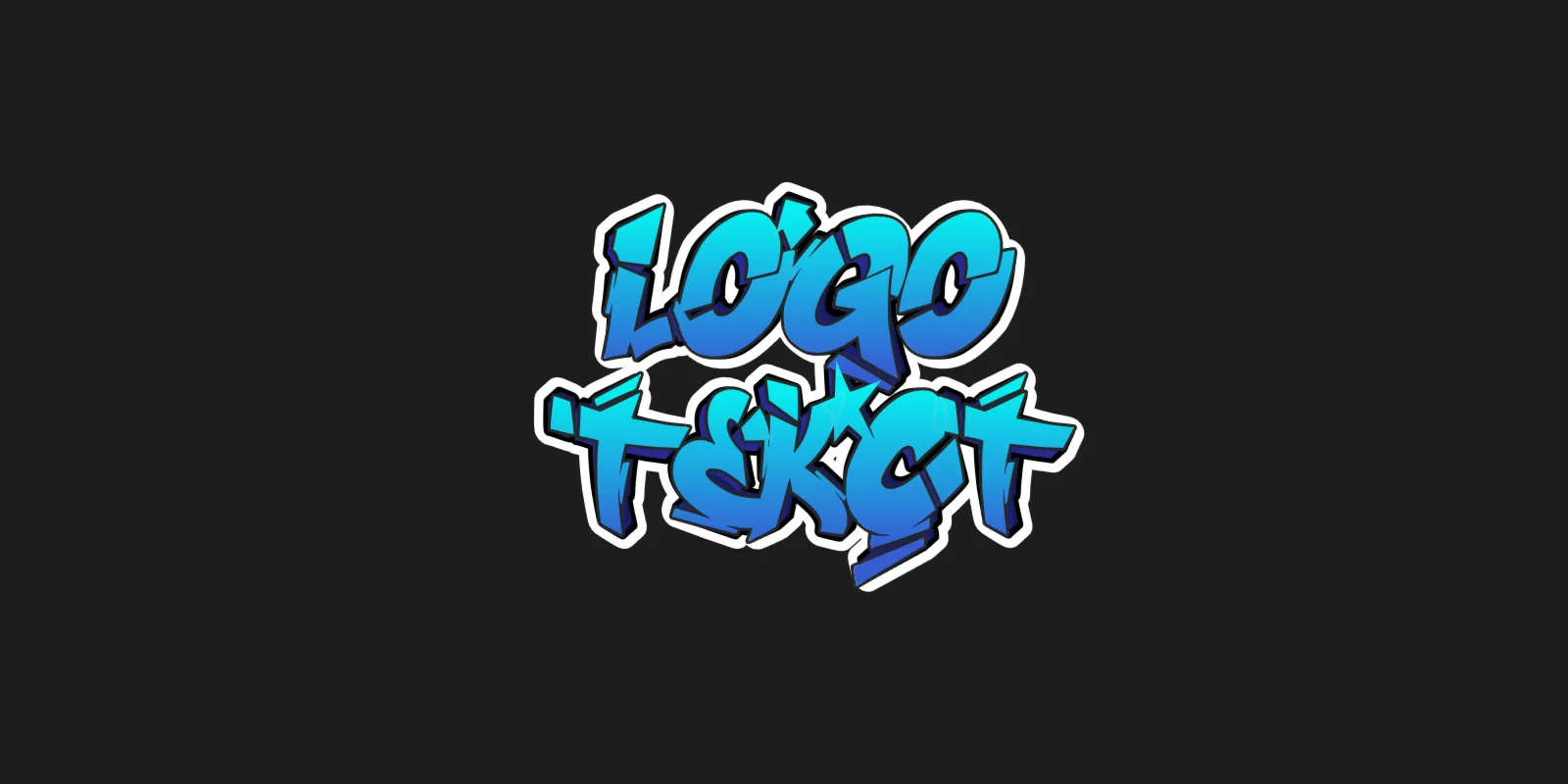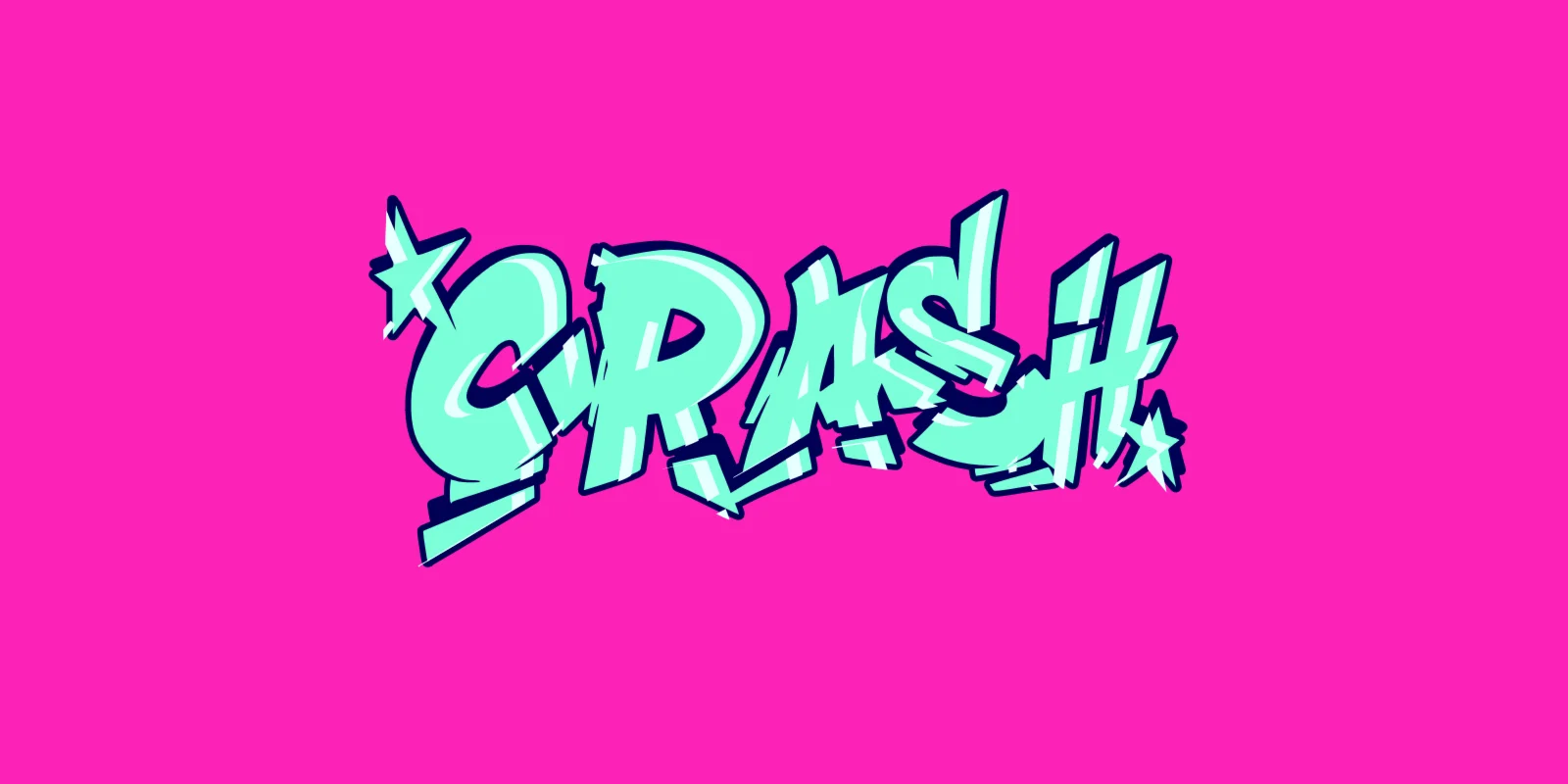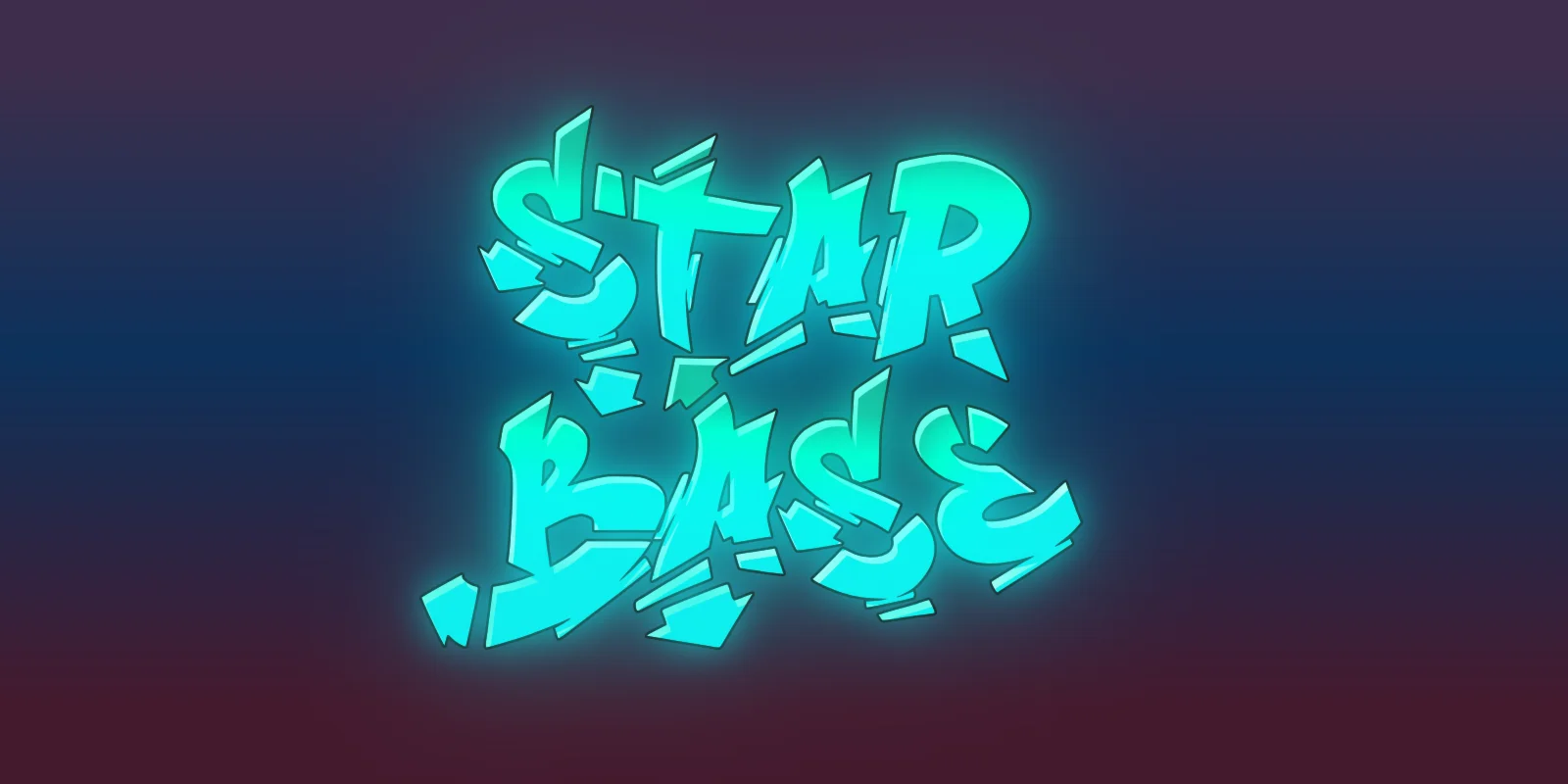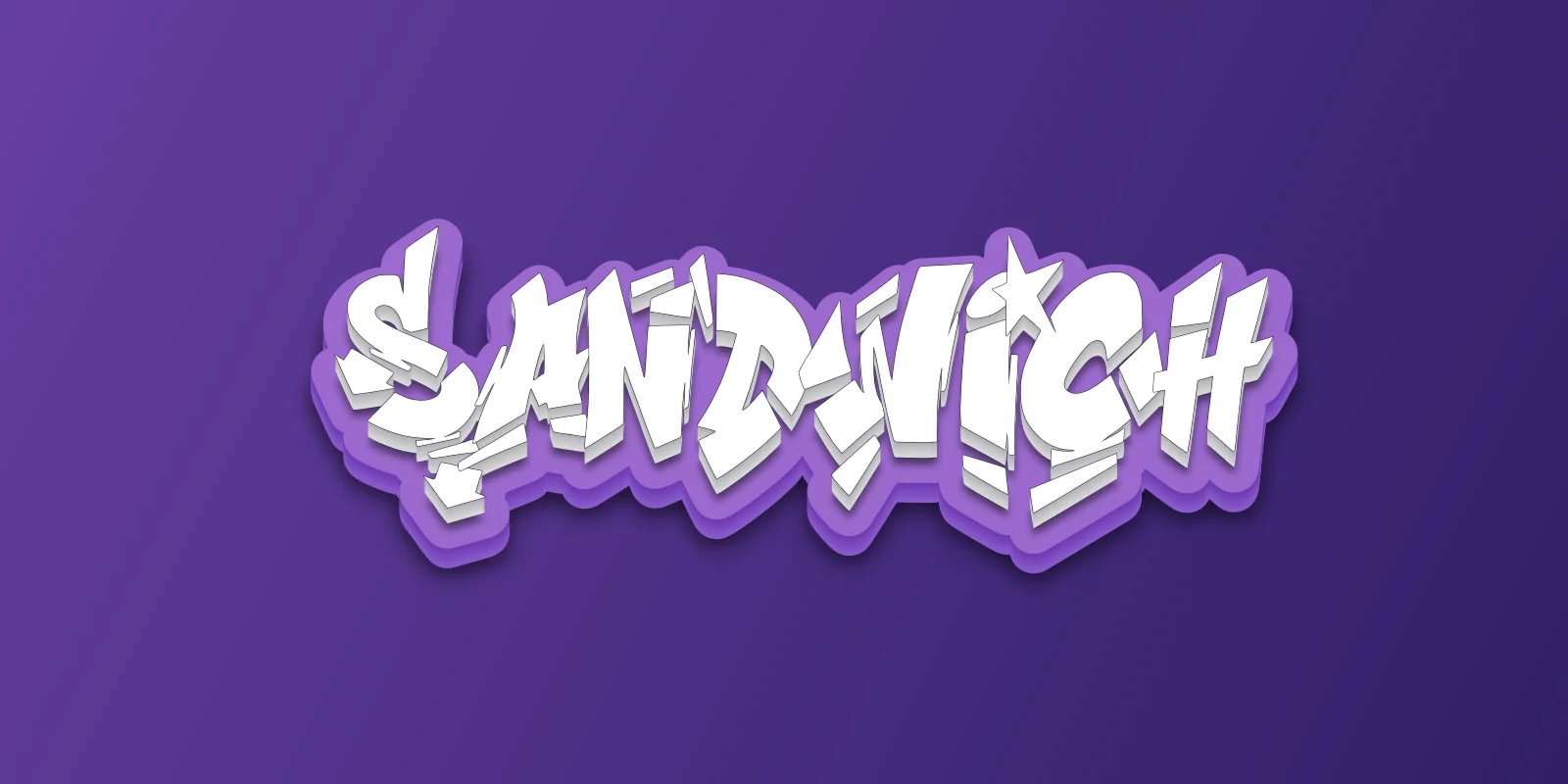
FontTextUp-StreetArtGT - это новый шрифт в стиле граффити включает русские и латинские буквы, который позволяет вам создавать тексты в визуальном стиле, характерном для уличного искусства. Шрифт был разработан с использованием элементов, характерных для граффити, таких как смешанные буквы, пересекающиеся линии, толстые контуры и живые цвета.
Этот шрифт отлично подойдет для создания заголовков, логотипов, приглашений, баннеров и любых других дизайнерских проектов, которые требуют эффекта уличного искусства. Шрифт имеет различные варианты начертания, включая полужирный, курсив, обычный, а также различные варианты цветовой палитры.
FontTextUp-StreetArtGT даст вашим проектам уникальный и оригинальный вид, который будет выделяться на фоне обычных шрифтов.